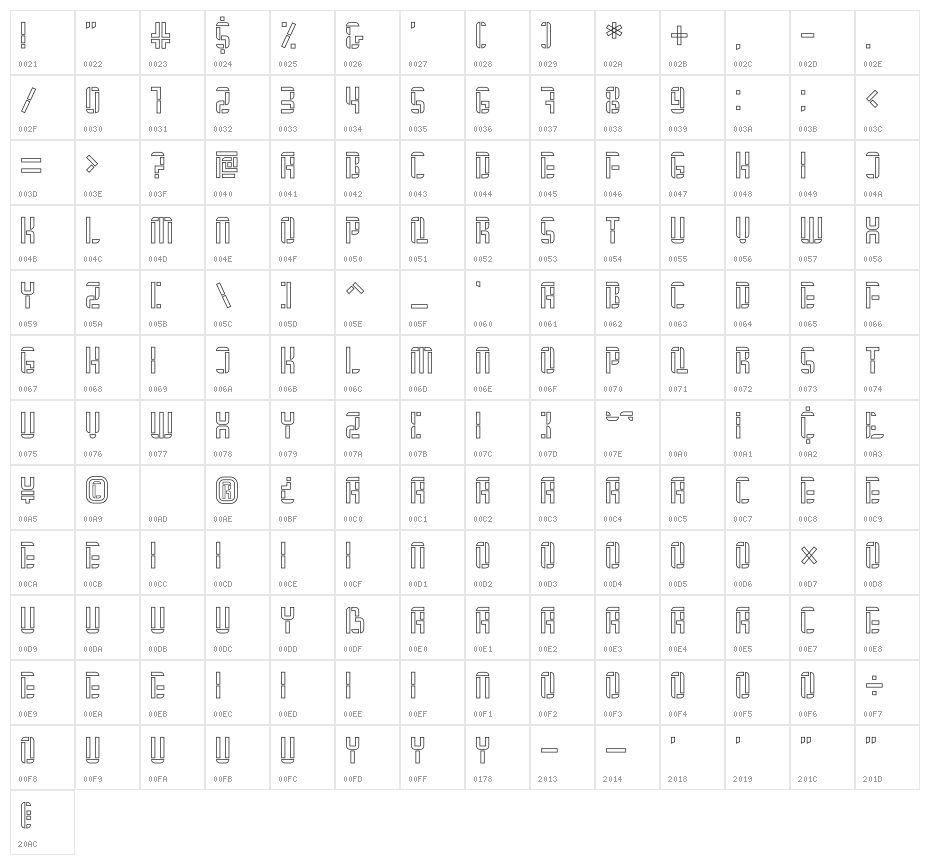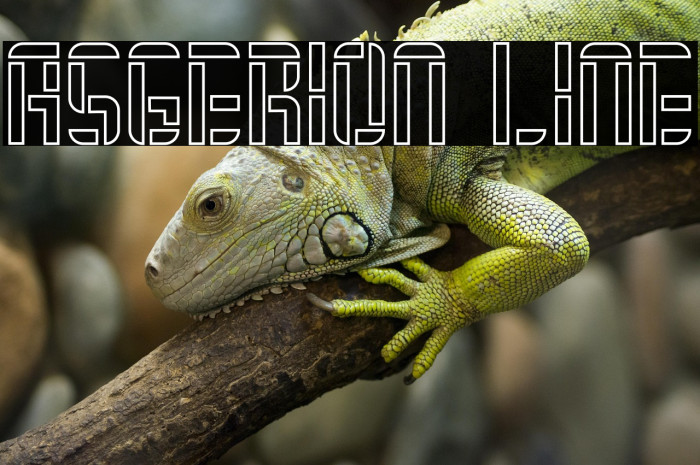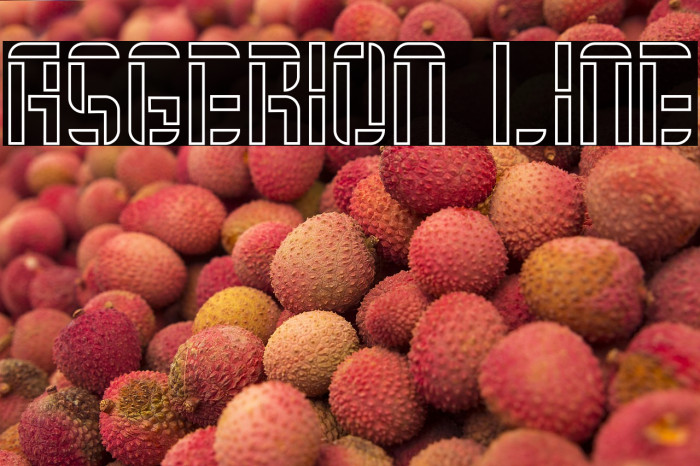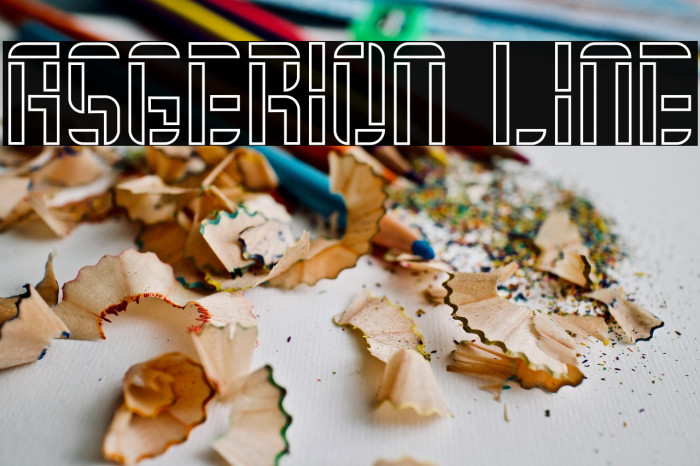
Asgerion Line Font
✎ Outline
| カテゴリ | Outline |
| おすすめプロジェクト | Ideal for technology-themed projects, sci-fi posters, branding for tech companies, and modern art installations. |
Asgerion Line